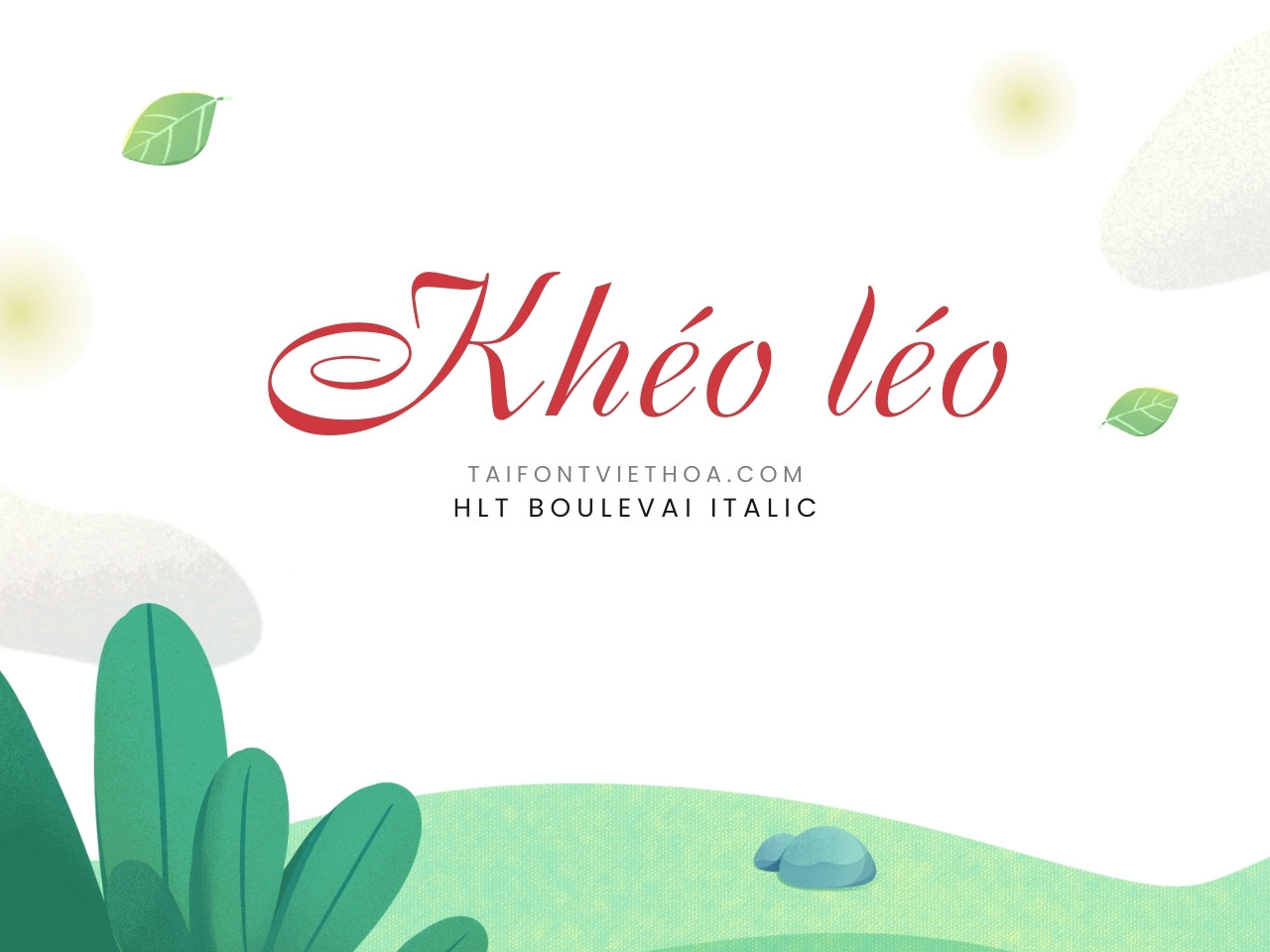
Giới thiệu về font Boulevard Italic – Thanh lịch và cổ điển theo phong cách nghiêng
HLT Boulevard Italic là phiên bản Việt hóa của font “Boulevard Italic” – một kiểu chữ thanh lịch mang phong cách retro kết hợp với đường nét nghiêng hiện đại. Font gốc được phát triển bởi Typodermic Fonts, một studio nổi tiếng với nhiều thiết kế mang âm hưởng cổ điển nhưng phù hợp xu hướng. Boulevard Italic là biến thể nghiêng của bộ font Boulevard nổi tiếng, hỗ trợ đầy đủ hệ ký tự Latinh, mở rộng tương thích hơn 70 ngôn ngữ toàn cầu.
Phiên bản Việt hóa được thực hiện bởi nhóm HLT Fonts với sự chỉnh sửa tinh tế, tối ưu dấu tiếng Việt theo tiêu chuẩn Unicode. Từng ký tự giữ nguyên tính thẩm mỹ nguyên bản, đồng thời bổ sung glyphs đặc trưng phục vụ người dùng Việt Nam trong các dự án thiết kế chuyên nghiệp. Font đã được taifontviethoa.com sưu tầm, tuyển chọn và thử nghiệm trong nhiều ứng dụng thực tế, phù hợp cho cả in ấn và thiết kế kỹ thuật số.
Đặc trưng thiết kế của HLT Boulevard Italic và ứng dụng thực tế
HLT Boulevard Italic mang đường nét serif nhẹ, cấu trúc chữ nghiêng về bên phải, tạo cảm giác chuyển động và nhấn nhá đầy tinh tế. Kiểu dáng thanh mảnh, các nét cong nhẹ nhàng giúp font toát lên vẻ duyên dáng, sang trọng mà không kém phần hiện đại. Font này rất lý tưởng để dùng làm tiêu đề, tagline, hoặc tên thương hiệu trong các thiết kế cần tạo dấu ấn đặc biệt.
Ứng dụng của HLT Boulevard Italic trải dài từ thiết kế thương hiệu thời trang, bao bì mỹ phẩm cao cấp, thiệp cưới, đến các ấn phẩm truyền thông, editorials hoặc poster nghệ thuật. Đặc biệt, phong cách nghiêng cổ điển khiến font này phù hợp với các ngành sáng tạo như quảng cáo, làm đẹp, wedding planner và nội thất cao cấp.